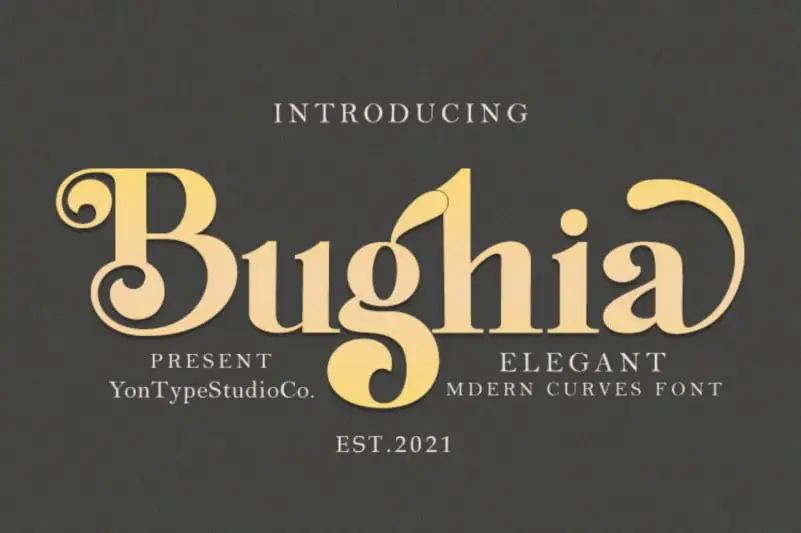
Bughia Serif Font – Download Grátis
A Bughia Serif é uma fonte serif com linhas bem arredondadas e curvas equilibradas. Esta elegante fonte remonta aos tempos dos livros de texto do passado, mantendo ao mesmo tempo um estilo moderno. Inspirada nos traços da escrita antiga, esta família de caracteres inclui tanto maiúsculas quanto minúsculas, e permite uma grande versatilidade para o design. Suas alternativas estilizadas permitem opções criativas sem comprometer a legibilidade, sendo ideais para headlines, logomarcas, cartazes, embalagens, camisetas de t-shirt e até mesmo postais. A Bughia Serif é um recurso gráfico perfeito para qualquer projeto visual que valoriza design e estilo combinando o clássico com a modernidade.